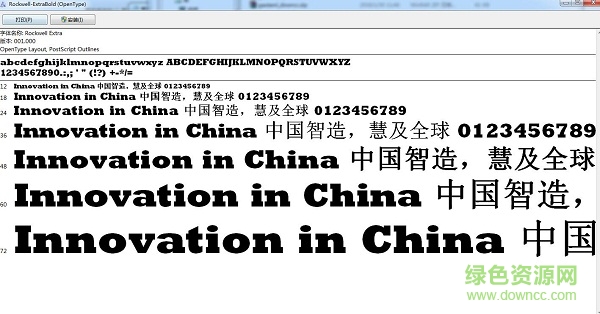
rockwell extra bold字体和rockwell bold字体是本站为大家搜集的两款经典粗衬线字体,又称埃及体,线条粗,结构严谨,适用范围发错了广泛,需要这款字体的小伙伴快来本站免费下载吧!
「衬线」指的是字形笔画在首位的装饰和笔画的粗细不同,所以「衬线」又被称为「字脚」这种装饰线的笔画设计多认为来源于古罗马纪念碑上的拉丁字母,1968 年 《The Origin of the Serif》中提到罗马字母最初被雕刻到石碑上之前,要先用方头笔刷写好样子,再照样雕凿。由于直接用方头笔刷书写会导致笔画的起始和结尾出现毛糙,所以在笔画开始、结束和转角的时候增加了收尾的笔画,也就自然形成了衬线。